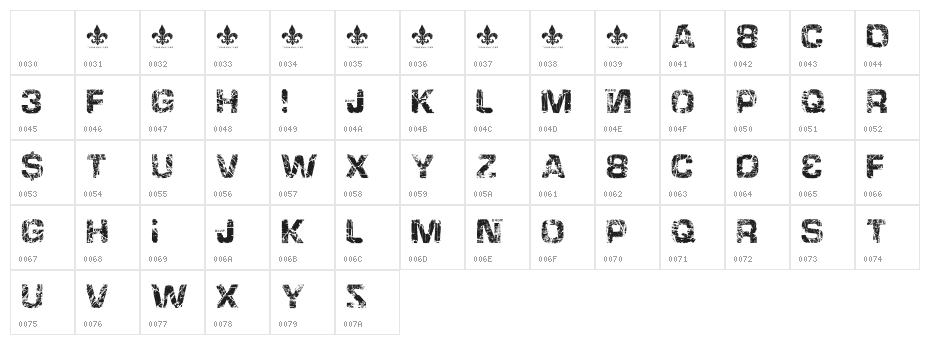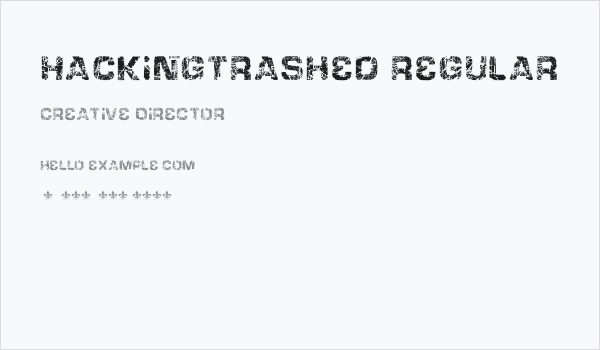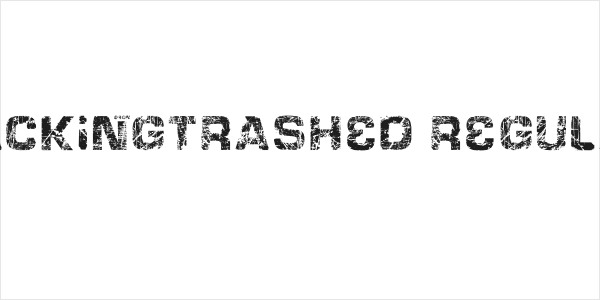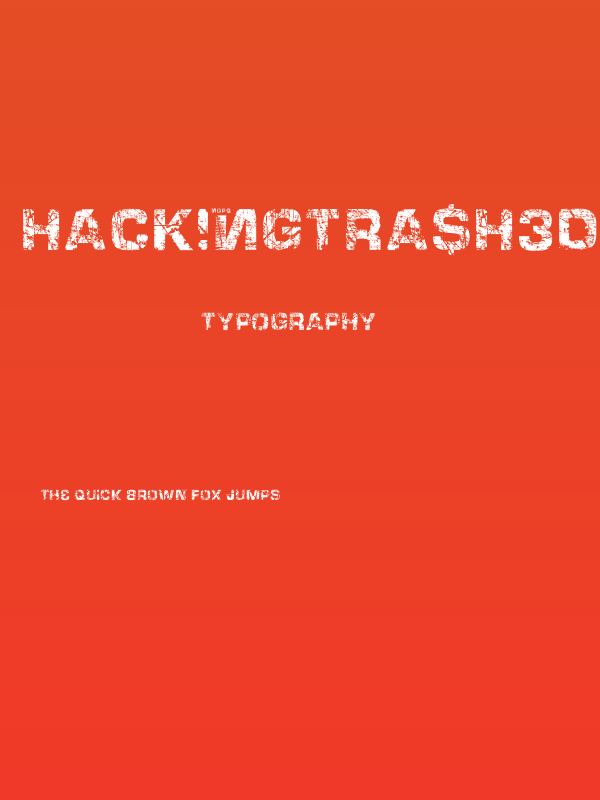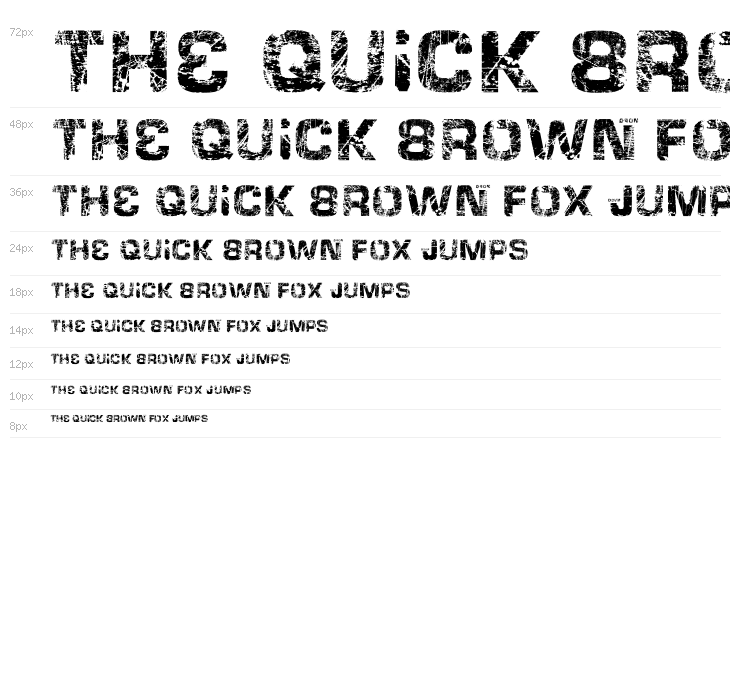
HackingTrashed Regular Font
✎ Distorted Eroded
| Proiecte propuse | Ideal for posters, album covers, urban-themed designs, and any project needing a raw, edgy look. |